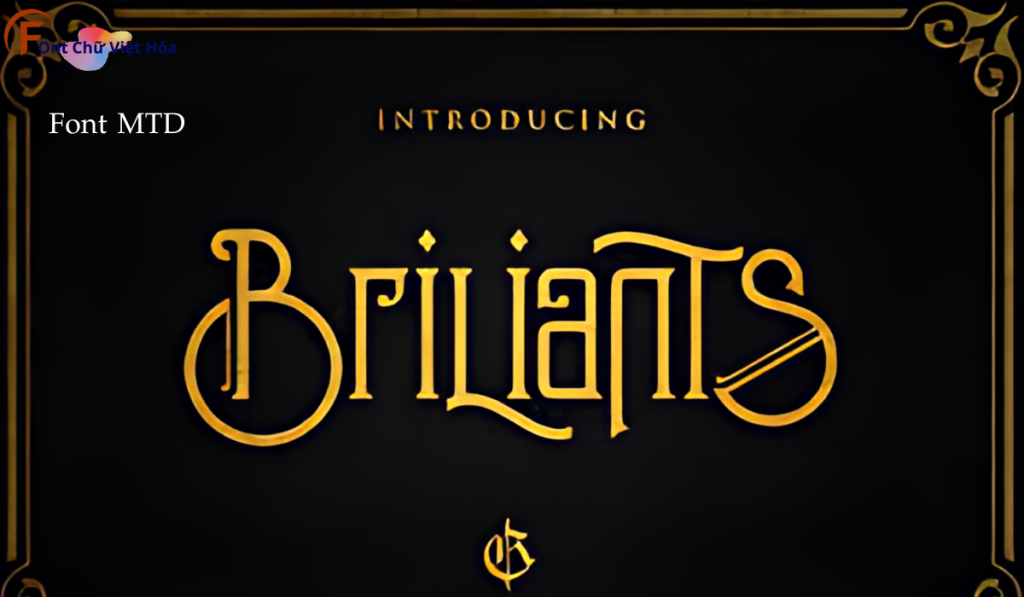
Font MTD Briliants Type Việt Hóa
Phân loại: Cá tính, độc đáo
Kiểu chữ: Có chân
Độ dày: Thường, in đậm
Font MTD Briliants Type Việt Hóa, thuộc bộ font MTD, mang phong cách hiện đại và thanh lịch, lý tưởng cho các dự án thiết kế như thiệp mời, bìa sách, và tài liệu văn phòng. Với các nét chữ có chân và độ dày đều đặn, Font MTD Briliants Type Việt Hóa không chỉ dễ đọc mà còn tạo cảm giác chuyên nghiệp và tinh tế. Việc Việt hóa font giúp người dùng dễ dàng tích hợp vào các thiết kế tiếng Việt, mang lại sự tiện lợi và nâng cao tính thẩm mỹ.